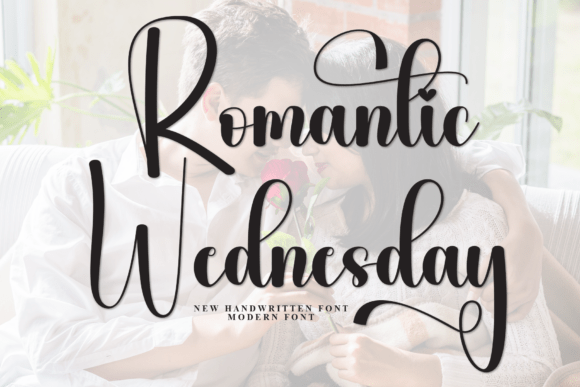
Romantic Wednesday
適切なデザイン要素を見つけるのは難しい場合がありますが、Romantic Wednesdayは作品を即座に引き立てる優れたコレクションを提供します。
POD(オンデマンド印刷)製品、結婚式の招待状、またはソーシャルメディアのグラフィックを作成している場合でも、Romantic Wednesdayは理想的です。